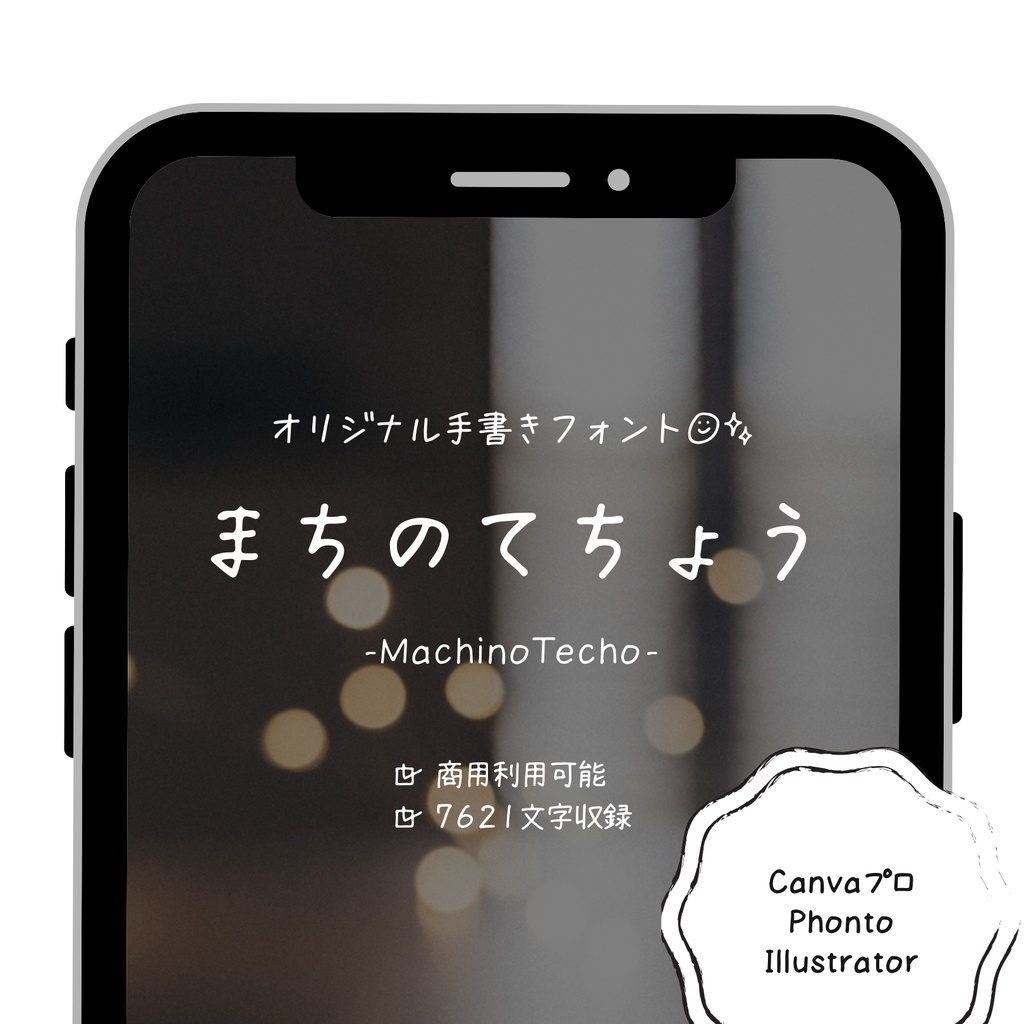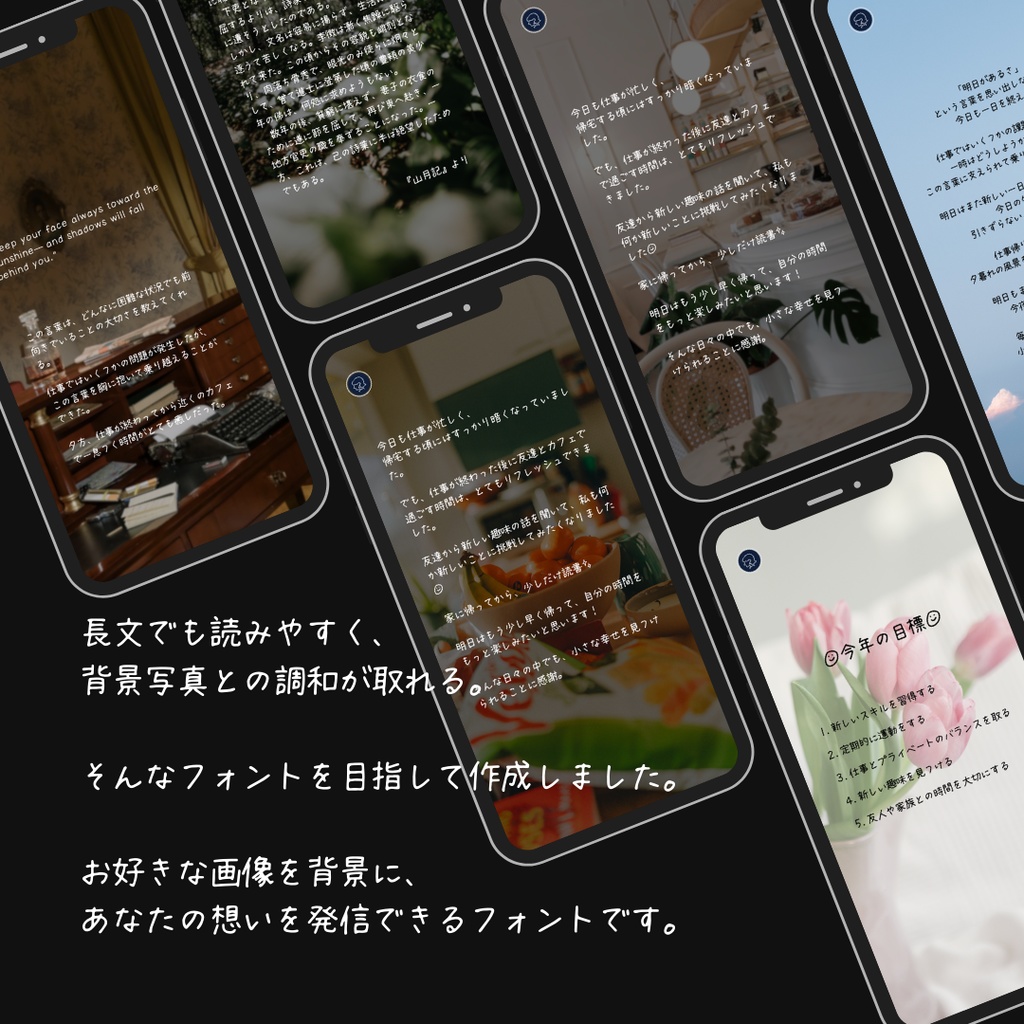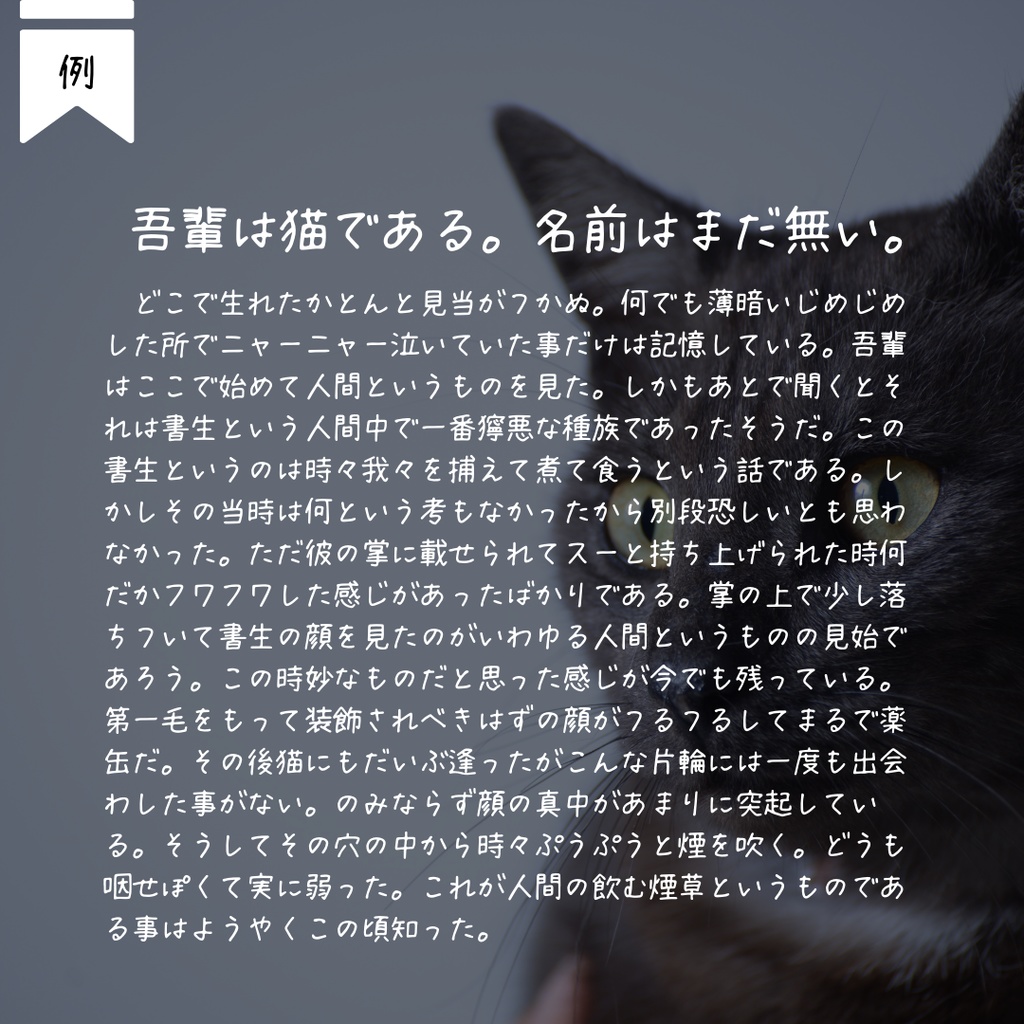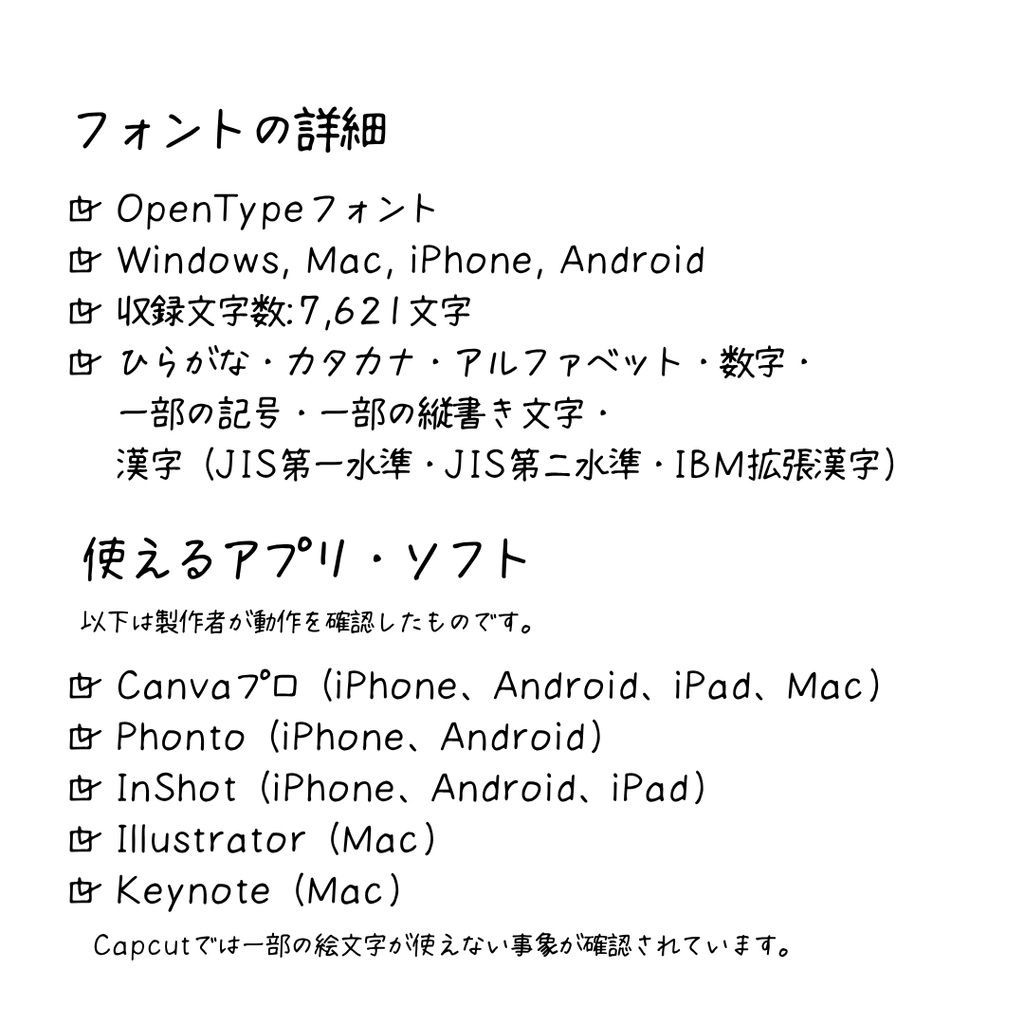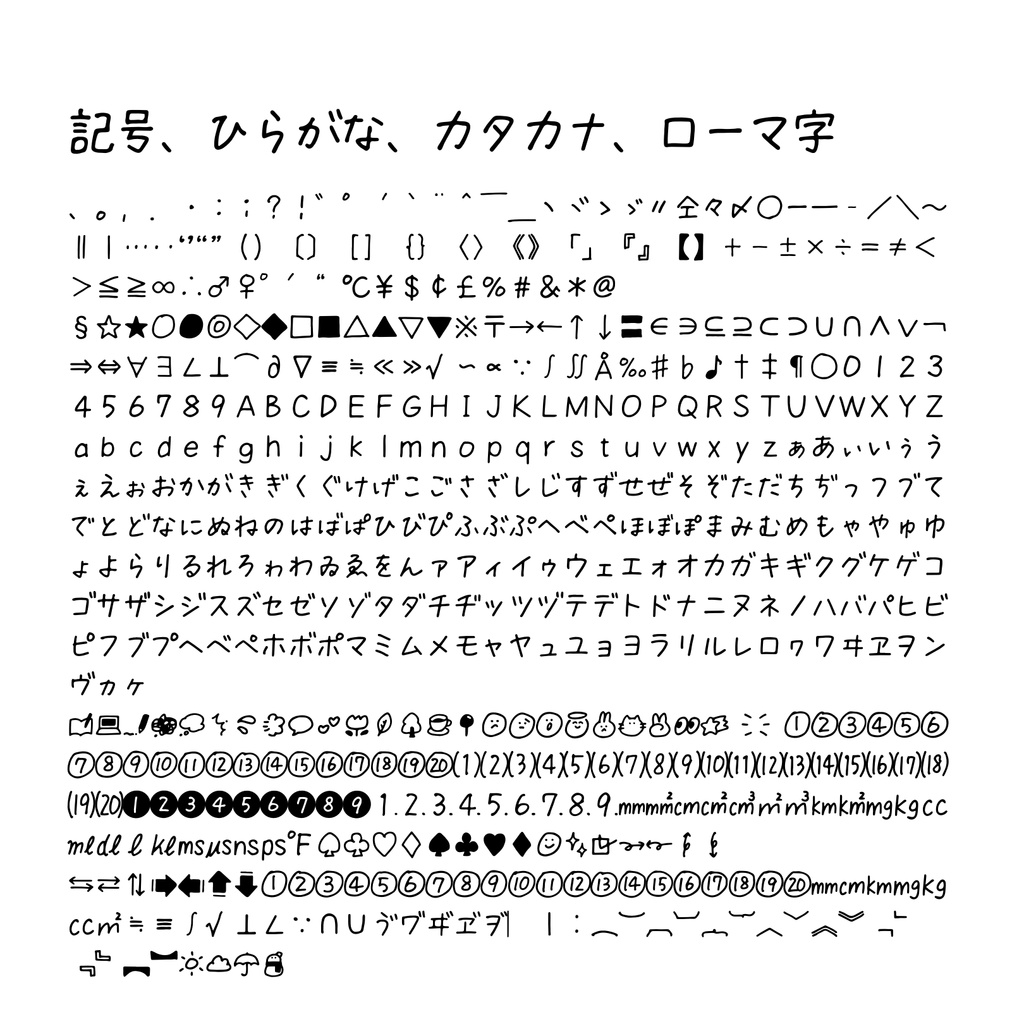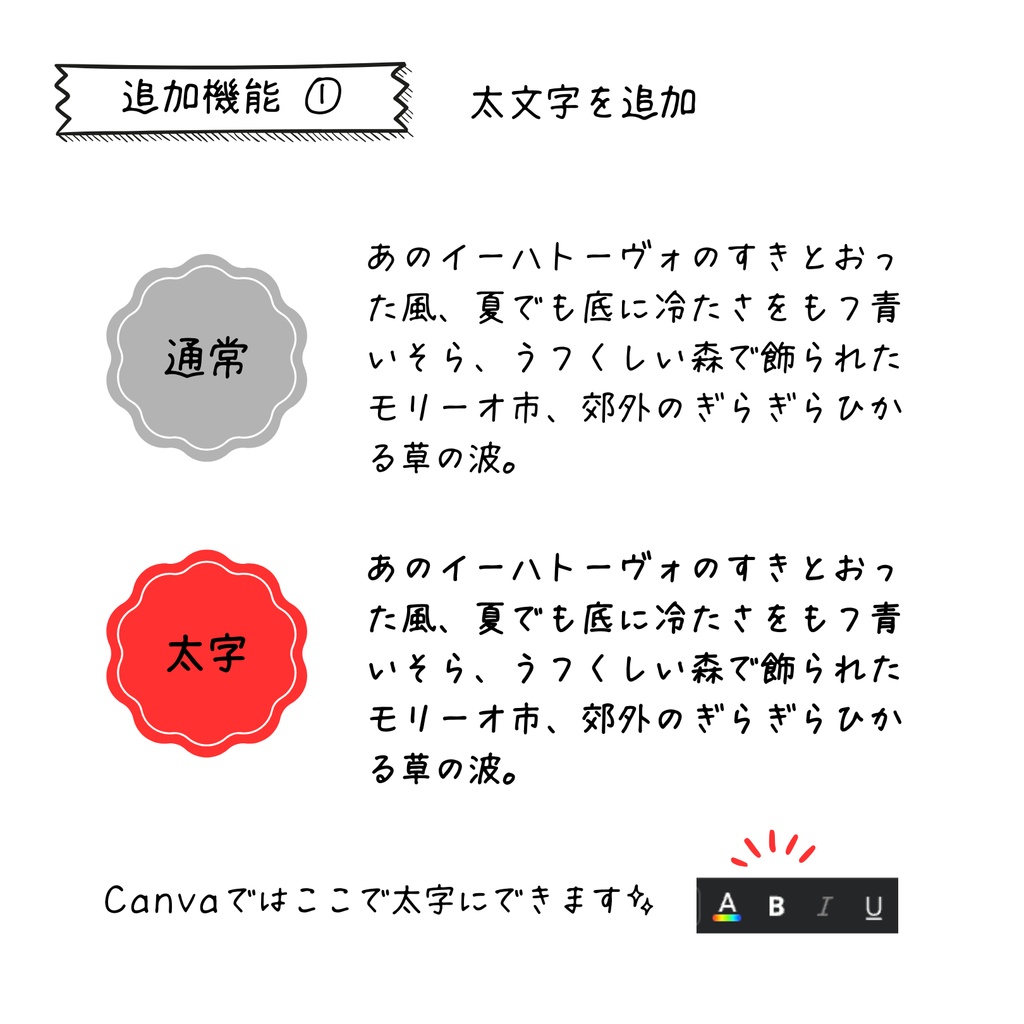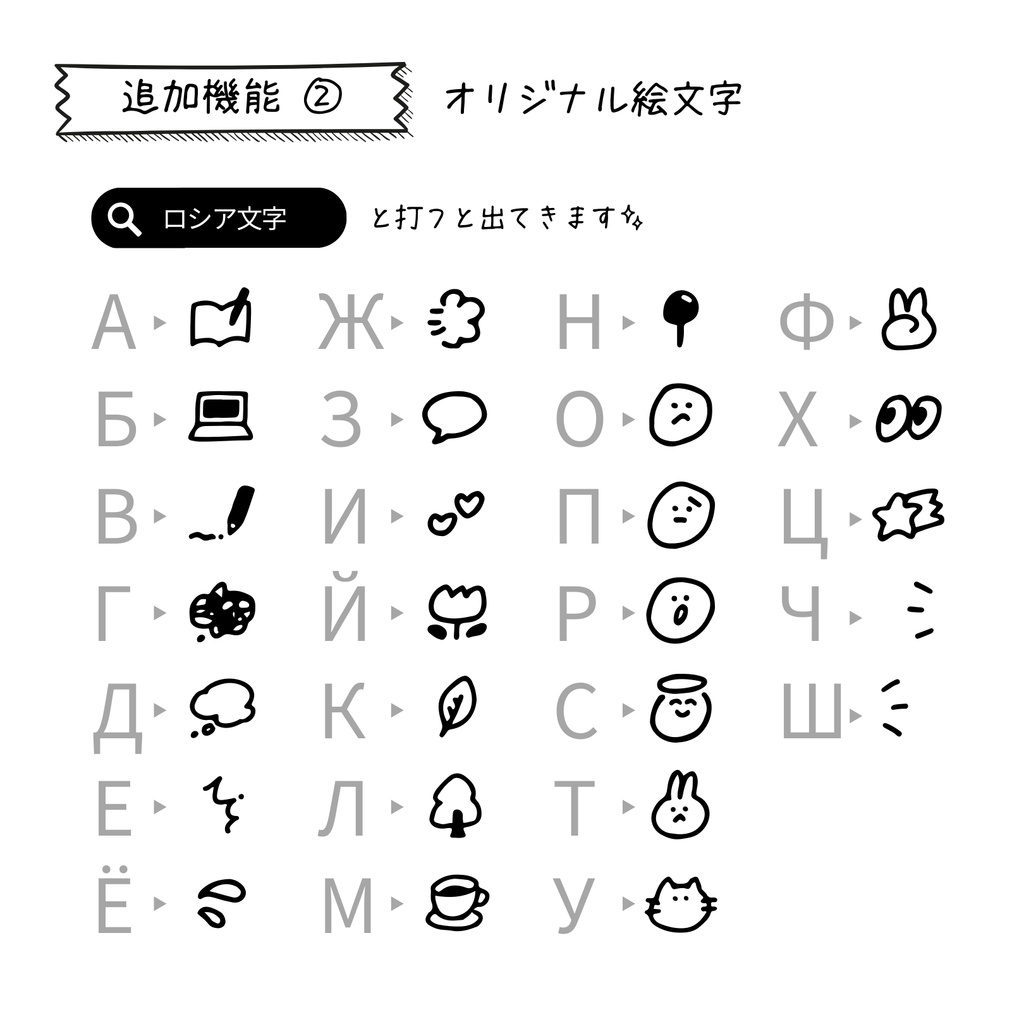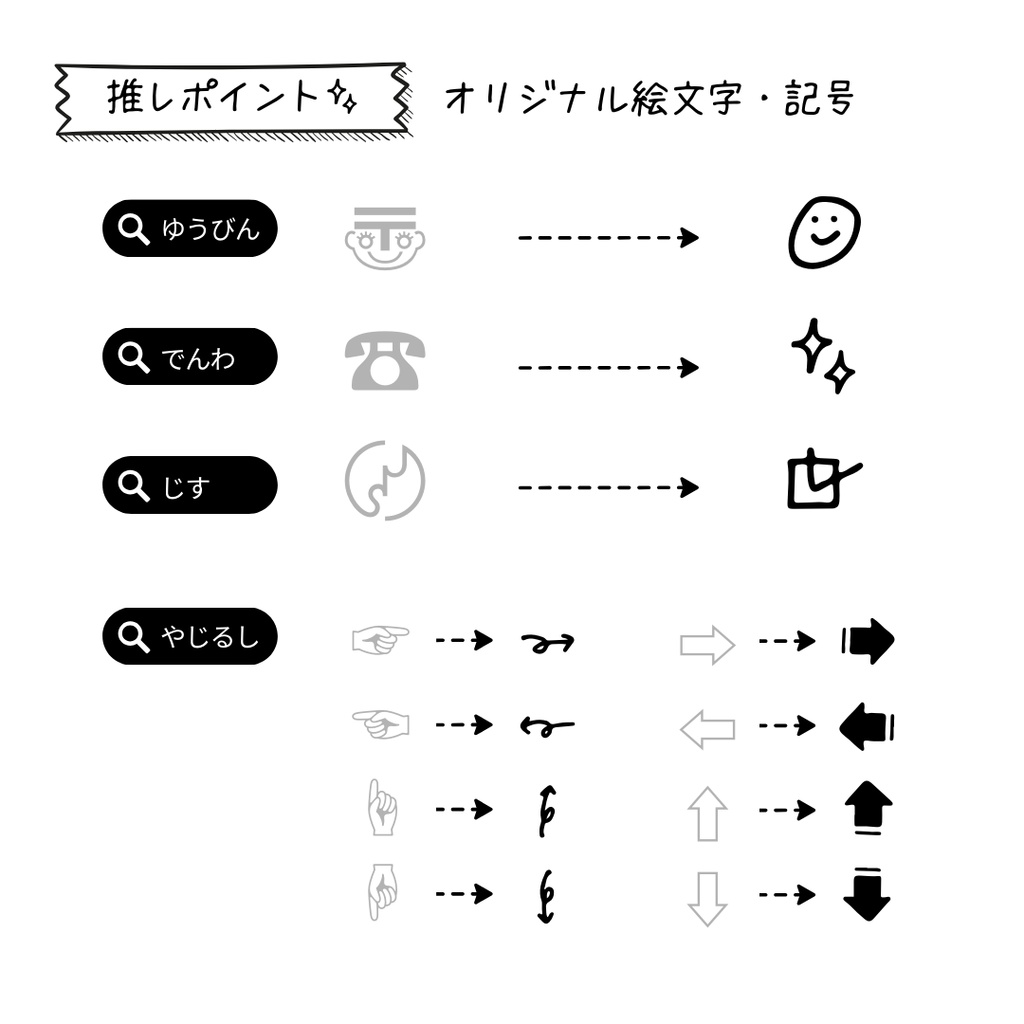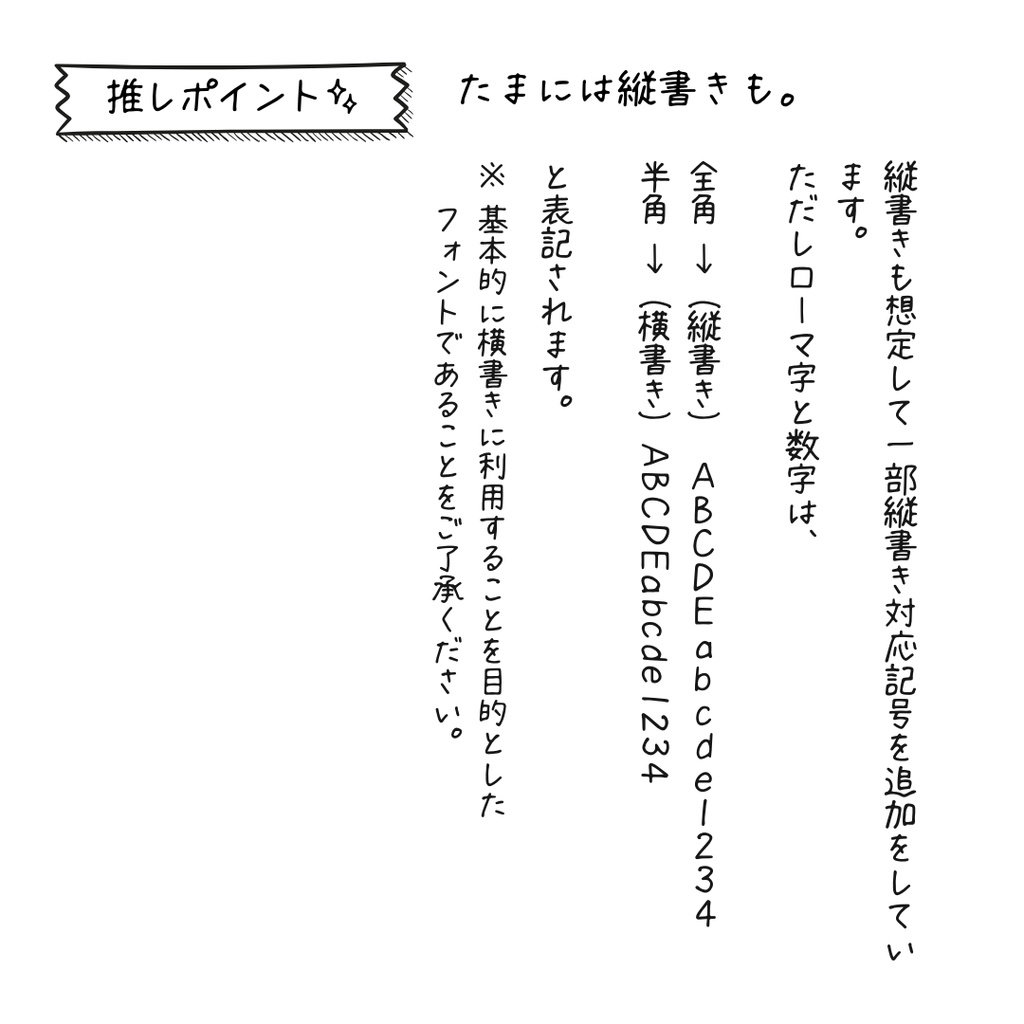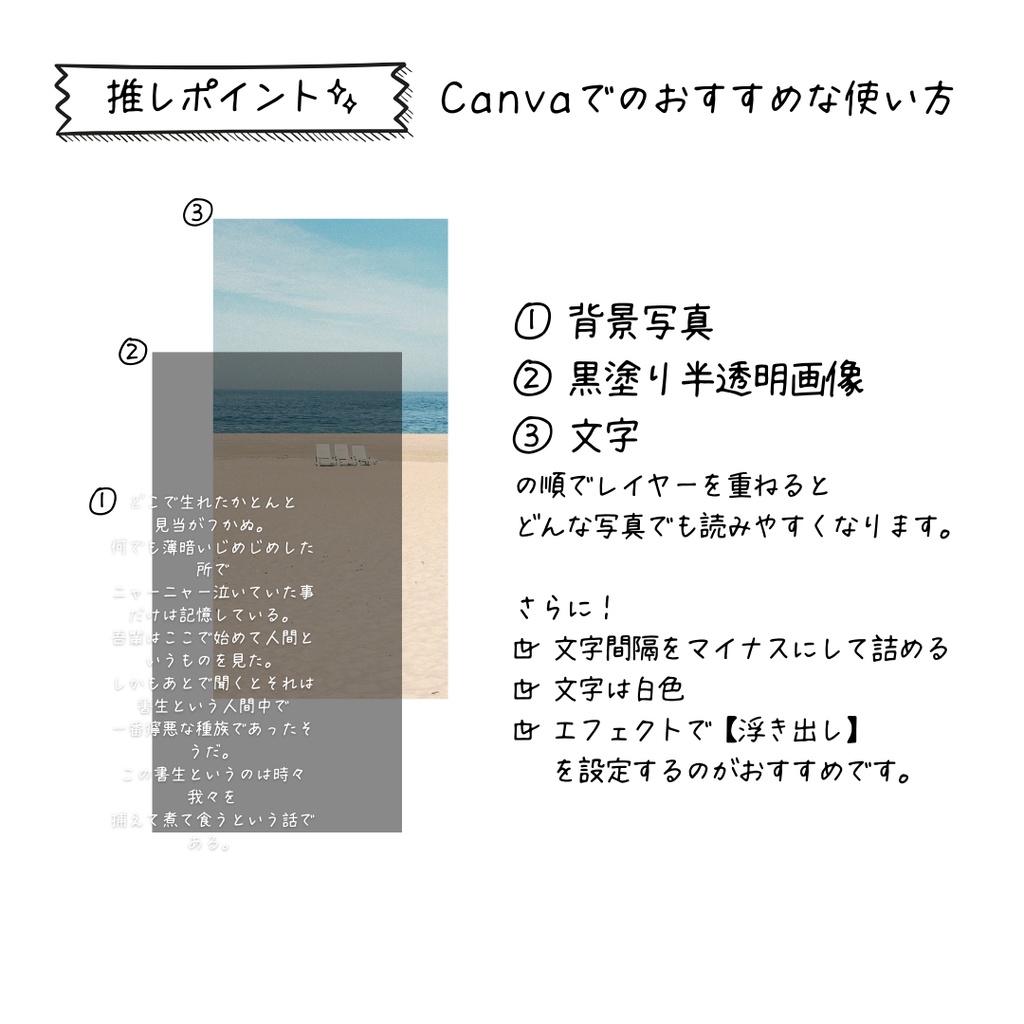
【商用利用可】手書きフォント「まちのてちょう」
iPadとApple Pencilを使って直筆で作成しました。 漢字も幅広くカバーしておりますので、 日常的なSNSの画像作成、創作活動などにお役立てください。 製作者は主にCanvaプロ、Procreate、Illustratorでフォントを活用しています◎ 初めてフォントを取り扱う方のために、 フォントをダウンロードした後の使い方ページも作成しました。 https://temporal-roquefort-94b.notion.site/103e5264ce9a47cc8e708378907fa245?pvs=4 【注意】 購入前に、商品画像内の ・フォントの詳細 ・使えるアプリ・ソフト ・使用許諾について ・禁止事項 ・免責事項 ・使用範囲 についてご一読ください。 ◼︎◼︎◼︎お知らせ◼︎◼︎◼︎ (2024年10月01日) 下記のバージョンアップを行いました! ・太字が追加 ・絵文字が26文字追加 すでに購入された方は、マイページから再度ダウンロードしてください。 (2024年10月10日) Windowsでフォントが重複してしまい、レギュラーとボールドの両方をインストールできない事象を解決しました。 (2026年6月17日) レギュラー版において、軽微な修正を行いました。 ボールド版において、パスが重なっている事象を修正しました。 ◼︎◼︎◼︎◼︎◼︎◼︎◼︎◼︎◼︎◼︎